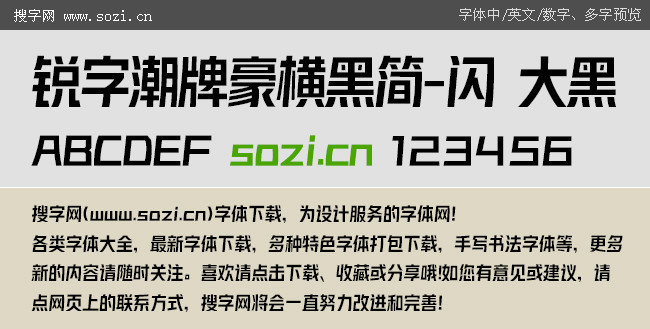
銳字潮牌豪橫黑簡-閃 大黑
搜字網提供一款銳字潮牌豪橫黑簡-閃 大黑中文字體下載,銳字潮牌豪橫黑是銳字字庫推出的一套個性藝術字體,共5個字重,字體穩定,優雅,堅固,看起來非常漂亮,整體效果非常均勻,字符齊全,可以廣泛使用,可用于出版和印刷,文學雜志,海報設計等應用。(本字體為個人非商用版,商用請聯系作者購買授權)